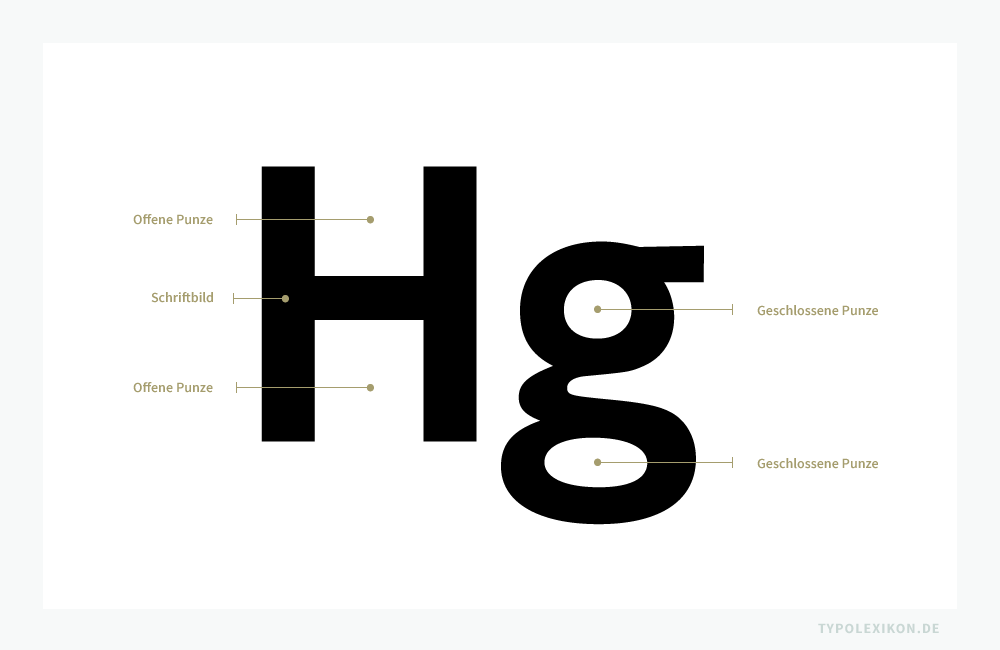
Punze
Typografischer Terminus für den nichtdruckenden Binnenraum eines Buchstabens, einer Arabischen Ziffer oder eines Sonderzeichens; Buchstabenbinnenraum. Das klassische Pendant zu einer Punze ist der nichtdruckende Außenraum eines Schriftbildes, das sogenannte »Fleisch«.
Eine Punze ist ein geschlossener oder offener Binnenraum eines Buchstabens, einer Arabischen Ziffer oder eines Sonderzeichens.
Ein in sich geschlossener Buchstabenbinnenraum, z.B. bei der Majuskel »Q«, wird als geschlossene Punze, ein geöffneter Buchstabeninnenraum, z.B. bei der Minuskel »v«, als offene Punze bezeichnet. Punzen zählen wie das Fleisch zu den nichtdruckenden Teilen eines Schriftbildes.
Die Typometrie der Punzen prägt maßgeblich den Grauwert und somit die Lesbarkeit einer Schrift bzw. letztendlich das geschriebene Wort. Die Form, Höhe und Breite der Punzen haben je nach Schriftstil und Schriftgrad unterschiedliche Auswirkungen auf den Grauwert.
Das deutsche Alphabet für Textschriften verfügt ohne Eszett und Umlaute über 26 Majuskeln und 26 Minuskeln, die – je nach Stilrichtung – mehrheitlich über mehr oder weniger ausgeprägte Punzen verfügen.
Majuskeln mit geschlossenen Punzen
B, D, O, P und Q
Majuskeln mit offenen Punzen
C, E, F, H, K, M, N, S, U, V, W, X, Y und Z
Majuskeln mit offenen und geschlossenen Punzen
A und R
Majuskel mit unterschiedlichen Punzenvarianten und -kombinationen
G
Majuskeln ohne Punzen
I, J und L
Minuskeln mit geschlossenen Punzen
b, d, o, p und q
Minuskeln mit offenen Punzen
c, h, k, m, n, s, u, v, w, x, y und z
Minuskeln mit offenen und geschlossenen Punzen
e
Minuskeln mit unterschiedlichen Punzenvarianten und -kombinationen
a und g
Minuskeln ohne Punzen
i, j, l und t
Punzenformen, Punzenweiten und Punzenhöhen sind von Schrift zu Schrift unterschiedlich. Die Form einer Punze kann sowohl rund (z.B. ellipsenförmig) als auch eckig (z.B. dreieckig) sein; die Formvielfalt ist groß. 1)
Abgesehen von spezifischen Klassifikationsmerkmalen (siehe Schriftklassifikation), orientiert sich die Form und Größe einer Punze in der Regel an der Strichstärke und der Breite eines Schriftzeichens, im besten Falle auch am Schriftgrad. So besitzen beispielsweise Schriften mit Optische Größen u.a. unterschiedliche Punzenrelationen, die vom Schriftgestalter:in (Type Designer) speziell auf Konsultationsgrößen, Lesegrößen, Schaugrößen und Ferngrößen bzw. Plakatgrößen abgestimmt wurden – was letztendlich zu einer deutlich besseren Lesbarkeit führt.
Semantisch ist der Terminus Punze (Buchstabenbinnenraum) von gleichnamigen Werkzeug Punze (Punziereisen) abgeleitet, einem Schlagstempel zur Metall- und Lederbearbeitung, der in der Typografie während der Epoche des materiellen Handschriftsatzes von Schriftschneidern (Stempelschneider) zur Herstellung von Schriftpatrizen bzw. Schriftmatrizen aus Metall verwendet wurde. Punziereisen gab es in unterschiedlichen Formen und Größen. Mit diesem Werkzeug konnten die Binnenformen einer Protoform (Stempel) exakt durchschlagen werden. Etymologisch leitet sich der Begriff »Punze« von »punzieren« ab, das aus dem mlat. »punctio« für »Stechen, Stich« entlehnt ist.
Thesen zur Punze
• Die Beschaffenheit der Punzen einer Textschrift beeinflusst den Grauwert eines Schriftsatzes und somit dessen Lesbarkeit.
• Eine Schrift sollte vom Anwender niemals »gedehnt« oder »gestaucht« werden, da dies u.a. die Architektur der Punzen und somit den Grauwert verändert. Derartige Modifikationen beeinflussen die Ästhetik und minimieren die Lesbarkeit.
• Unterschiedliche Schriftgrade und Leseabstände verlangen im Idealfall unterschiedliche Punzen. Optische Größen erhöhen deshalb signifikant die Lesbarkeit einer Schrift.
• Variable Fonts werden den Trend in der Schriftgestaltung verfestigen, korrespondierende Schriftschnitte nicht mehr separat zu entwerfen – also auch keine individuellen Punzen mehr zu konstruieren –, sondern automatisch zu interpolieren, was in der Summe einen Qualitätsverlust bei Auszeichnungsschnitten darstellt.
• Die Breite der offenen Punze der Minuskel »n« – unabhängig davon, ob es sich dabei um eine Schrift mit oder ohne Serifen handelt – kann in einer Lesegröße als Referenz für den idealen Wortzwischenraum dienen.
• In der analogen und digitalen Typografie werden Punzen, Fleisch sowie Vor- und Nachbreiten unterschiedlich bewertet, was bei der Rezeption von älterer typografischer Literatur meist zu Fehlinterpretationen führt.